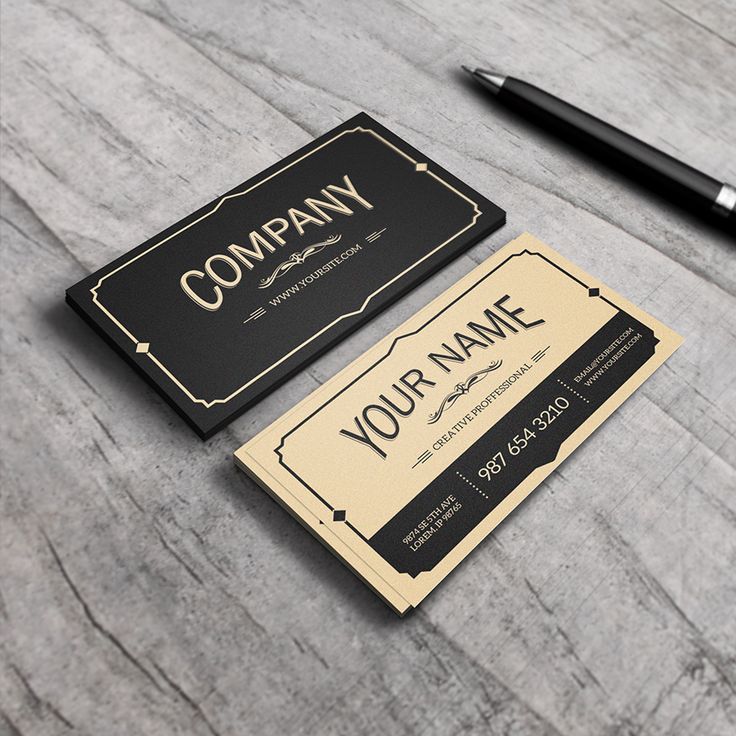
В современном мире бизнеса не обойтись без визитных карточек. В них содержится в лаконичной форме вся контактная информация о фирме или частном лице. Визитка – ваша идентификация в обществе. Визитными карточками обмениваются на деловых встречах, беседах, при знакомстве с будущими компаньонами и клиентами, при прощании; их раздают на выставках и презентациях.
Студия ИДЕЯ обязательно предложит вам различные варианты визиток. Личные визитки используются непосредственно тем лицом, контактные данные которого указываются на визитной карточке. Корпоративные визитки содержат информацию и контактные данные самой фирмы или компании. Такие визитки чаще всего используют на презентациях и выставках, когда нужно представить компанию, а не конкретное лицо.
Несмотря на разнообразие визитных карточек, оные не должны быть стандартными белыми прямоугольниками с черными надписями.
Цветовая гамма должна выделяться и запоминаться людям. В то же время цвет визитки не должен быть «кричащим», то есть не должен напрягать зрение компаньона или клиента. Ярко-салатовые, ядовито-розовые или сочные оранжевые (цвета, используемые в гелевых ручках) раздражают зрение и не дают сконцентрироваться на тексте визитки.
Также не стоит использовать сочетание красного и синего цветов. Как доказано учеными, эти цвета в сочетании «вибрируют» в человеческом восприятии. Вышеперечисленные цвета могут вызвать негативное восприятие адресата к вашей визитке. Если все же эти цвета используются в вашем стиле компании, то следует их «разбавить» стандартными оттенками или снизить их «ядовитость», сделав цвет более мягким.
Обратим внимание на шрифт. При использовании цветовой гаммы (не темной) лучше остановиться на черном цвете шрифта – это облегчит чтение и запоминание информации. Шрифт на визитке не должен быть мелким. Кегль (размер шрифта) должен быть не ниже 7-8 пунктов – это позволит прочитать информацию быстро, не всматриваясь в текст. Шрифт может быть любой, но он должен легко читаться. Желательно не использовать шрифты «рукописные» — их тяжелее прочесть, и витиеватые (с завитками). Красивые каллиграфические шрифты можно использовать только с крупным кеглем – в названии компании или в ФИО контактного лица.
Обратная сторона визитки вызывает много споров, как среди заказчиков, так и среди дизайнеров. Большинство дизайнеров советуют заказчикам оставить обратную сторону визиток пустой. Ведь на пустой стороне можно записать дополнительные данные – адреса, время работы, дополнительные номера телефонов и адреса электронной почты. Заказчики же хотят вместить в визитки как можно больше информации и полностью занять обратную сторону. Рассмотрим эту проблему подробнее.
1. Обратную сторону визитки можно оставить белой. Тогда адресат, которому вы дали визитку, может внести на нее дополнительную информацию или пометки. В таком случае желательно, чтобы обратная сторона была обычной бумажной и белой.
2. На обратной стороне можно поместить слоган компании, если это корпоративная визитка или частное лицо является сотрудником, и предоставляет информацию или услуги этой компании.
Тогда и лицевую и обратную сторону визитной карточки можно оформить в едином стиле.
3. Если ваша фирма или компания находится не на центральных улицах города, то на обратной стороне визитки можно поместить небольшую карту с местоположением вашей фирмы или компании. Это облегчит путь вашим компаньонам и заказчикам.
4. Сосредоточьтесь на улучшении читаемости
Неважно, насколько красиво выглядит шрифт на экране вашего компьютера, если никто не сможет прочитать его, когда визитная карточка будет распечатана на бумаге. Прежде чем остановиться на шрифте, сделайте несколько тестовых распечаток на домашнем принтере, чтобы увидеть, как шрифты выглядят в разных размерах, и найти идеальные настройки, обеспечивающие наилучшее взаимодействие с пользователем.